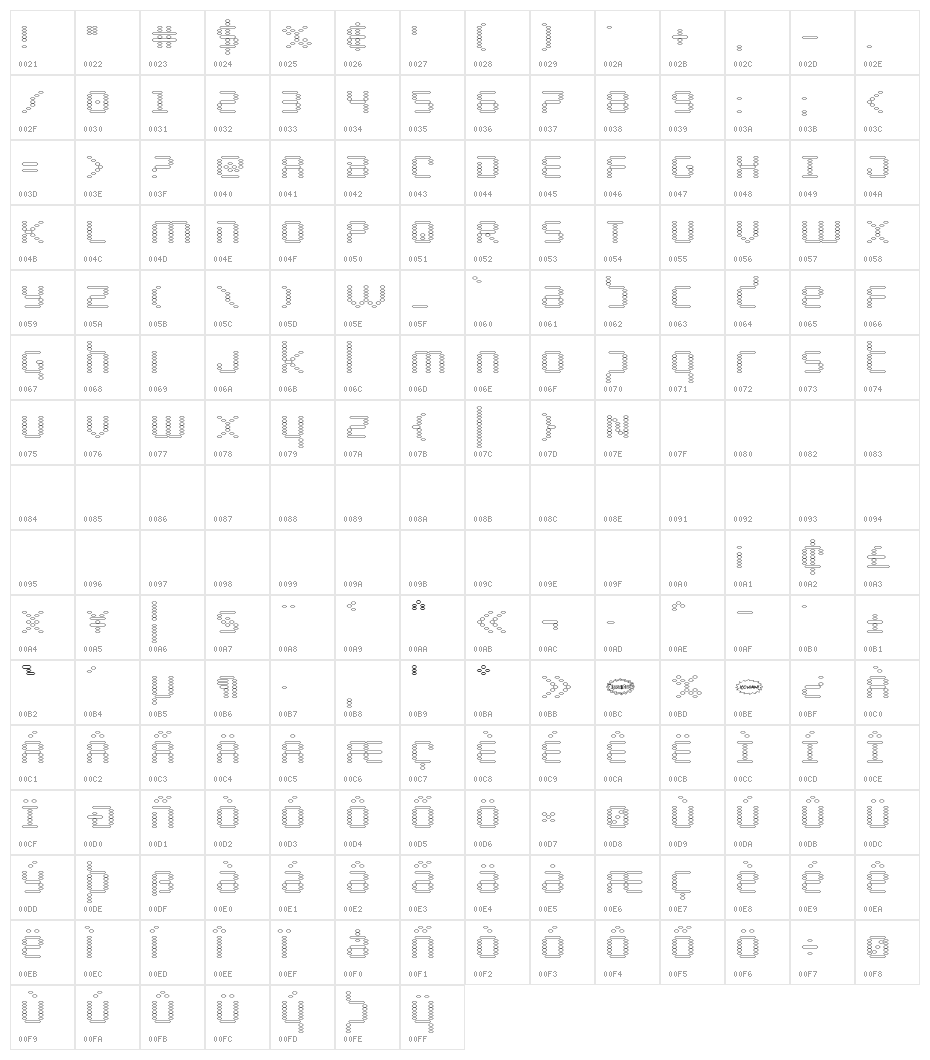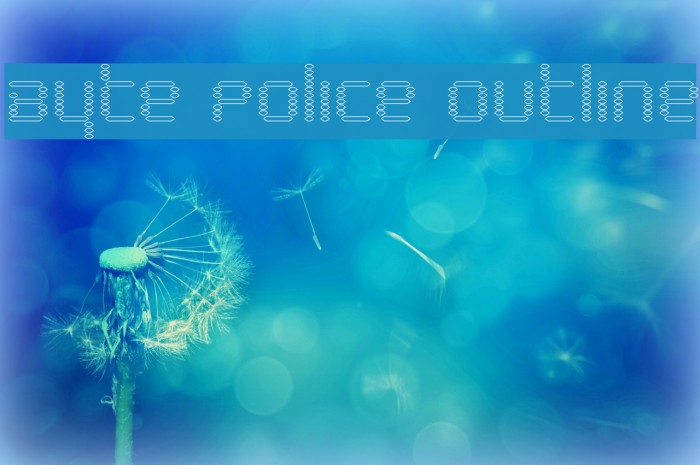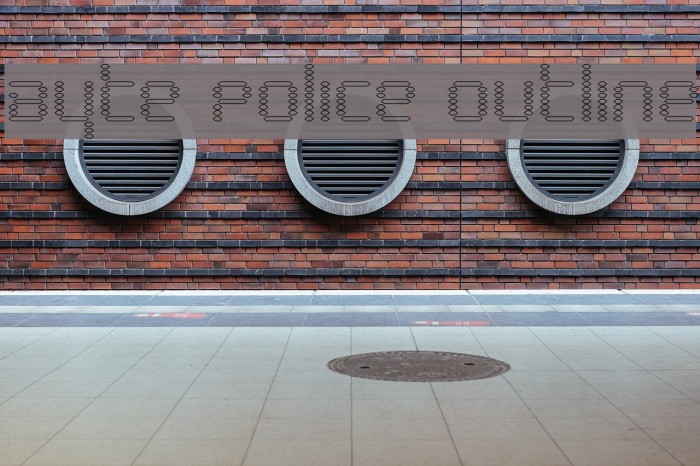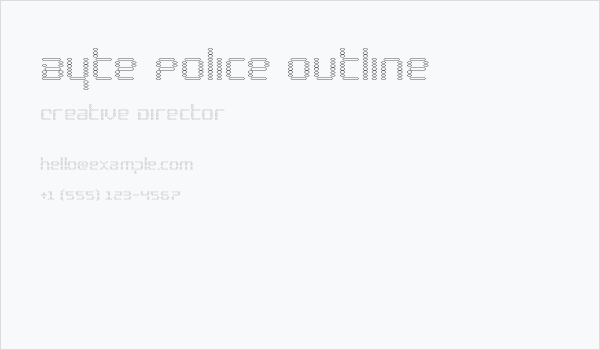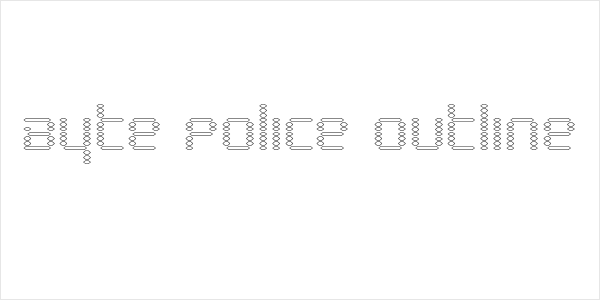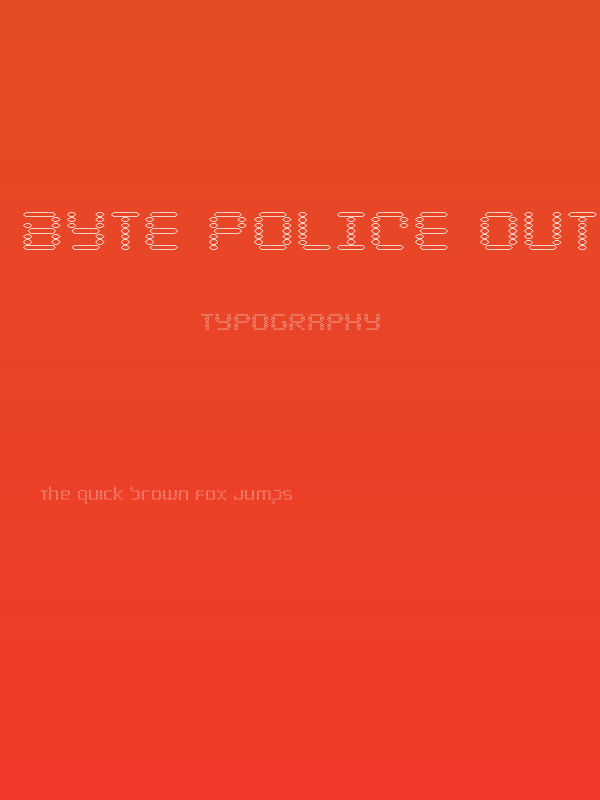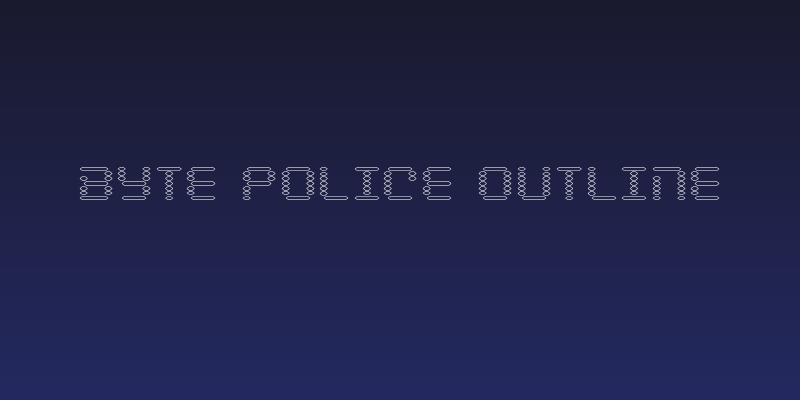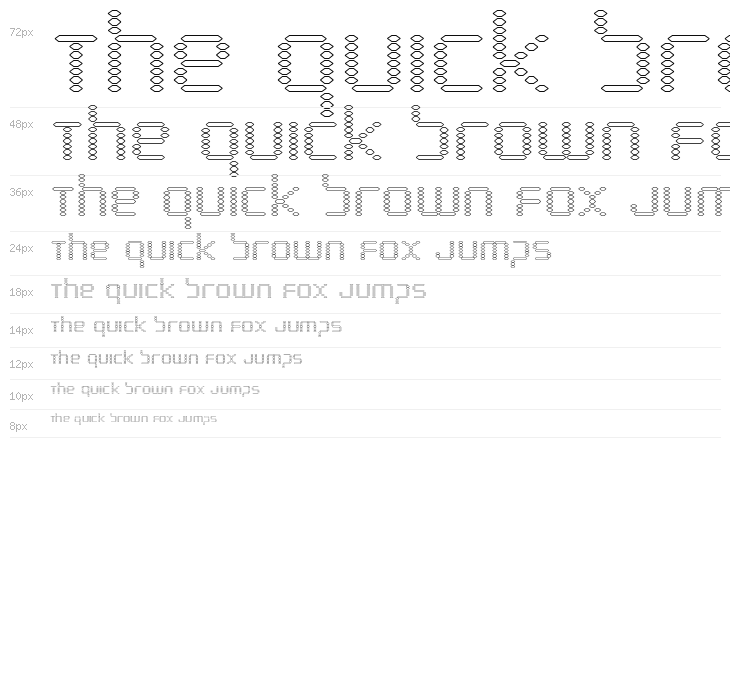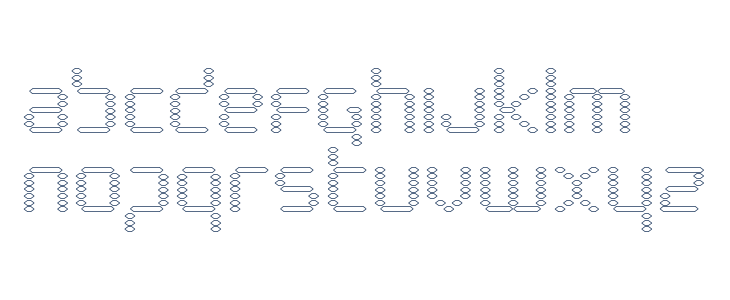
Byte Police Outline Font
| Progetti proposti | Ideal for tech branding, digital art projects, sci-fi themed designs, and modern advertising campaigns. |